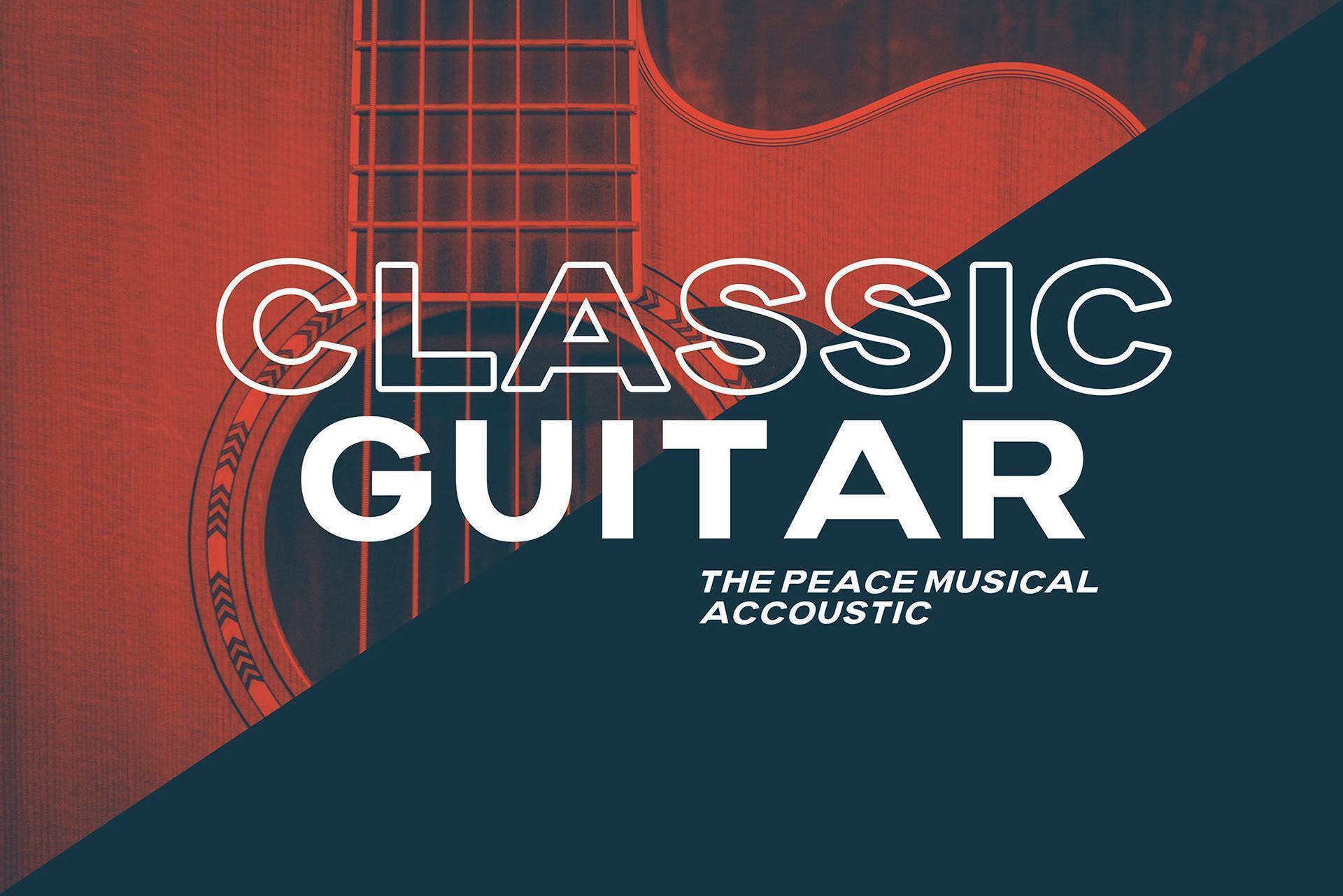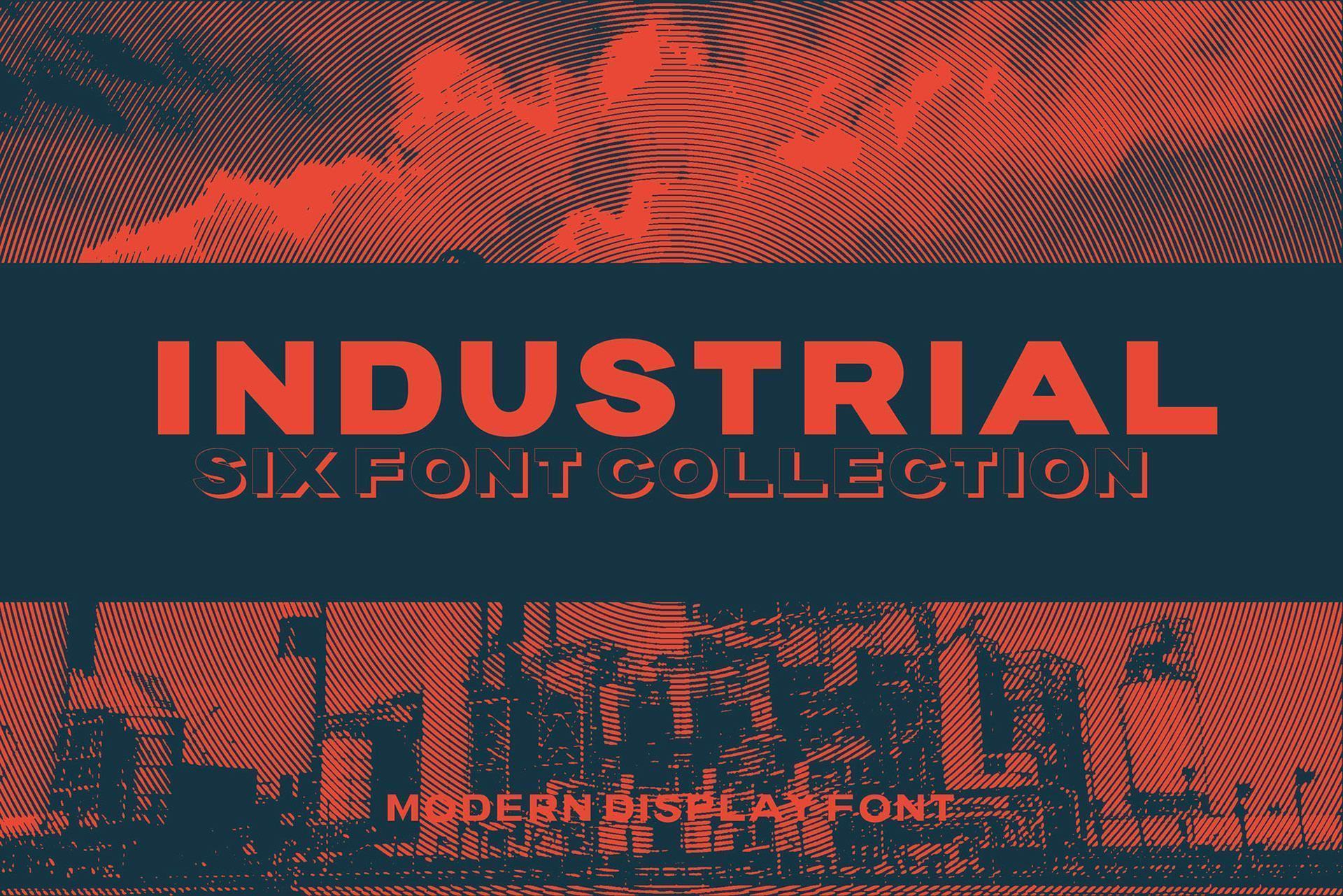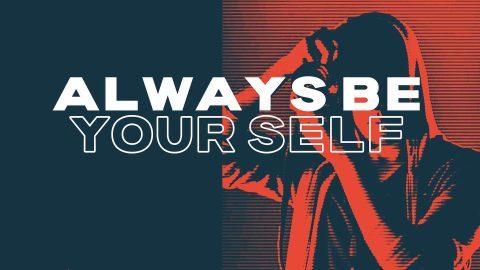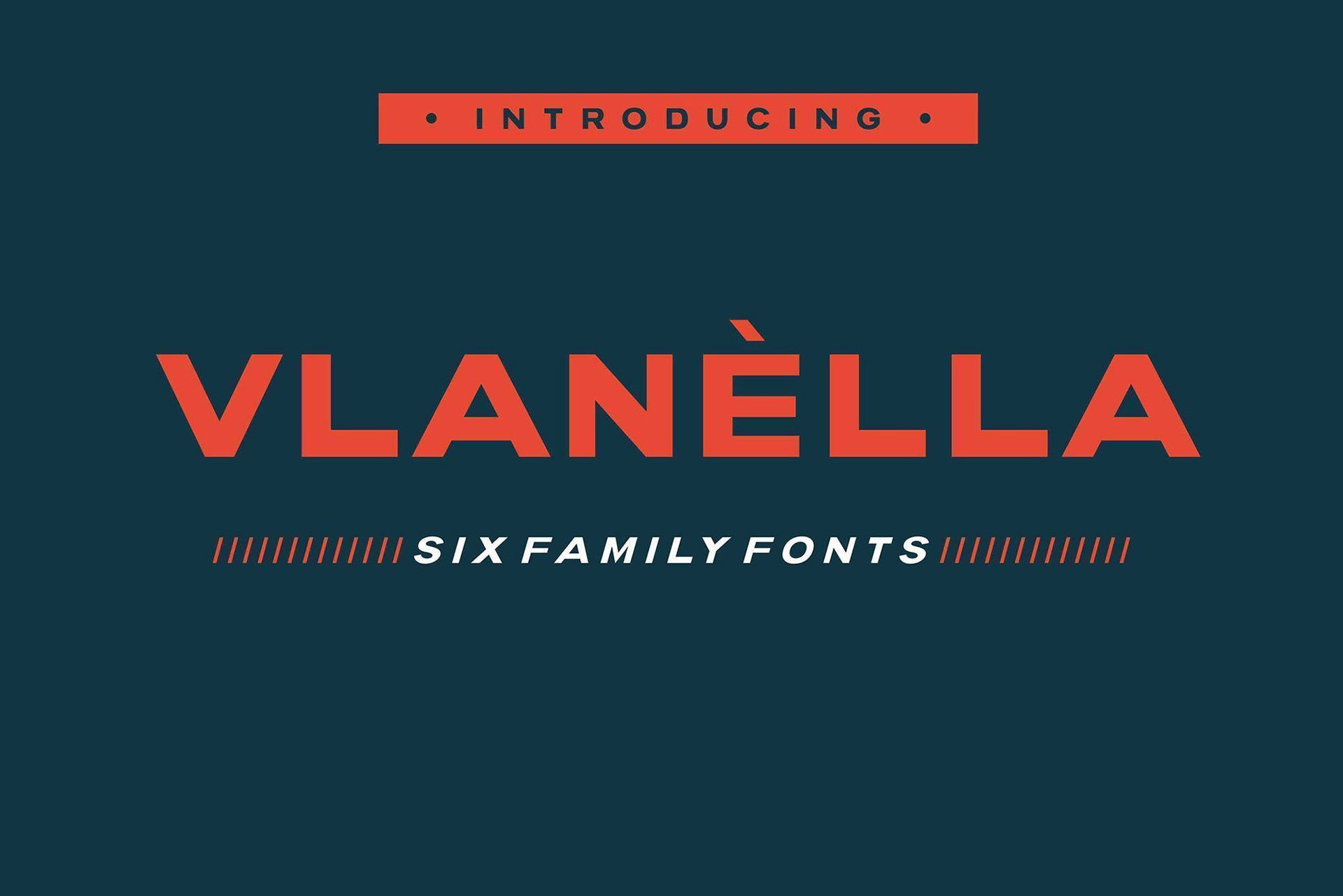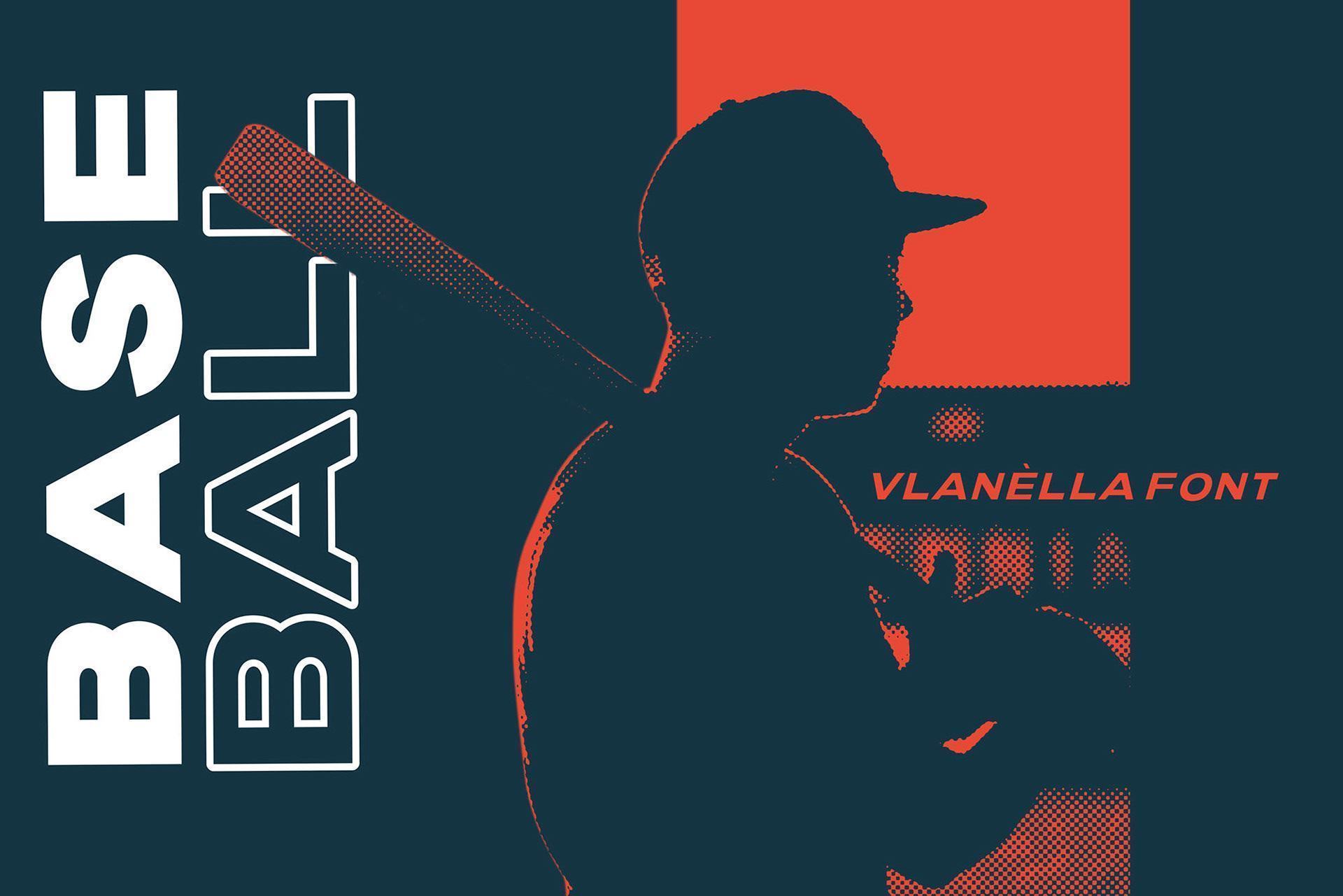
Vlanèlla là một họ phông chữ đầy phong cách với 6 kiểu khác nhau. Đó là một kiểu chữ đậm, thanh lịch và có thể phù hợp cho cả các dự án hiện đại và cổ điển. Phông chữ sans serif này rất linh hoạt và có thể phù hợp hoàn toàn với các dự án in ấn và kỹ thuật số của bạn.